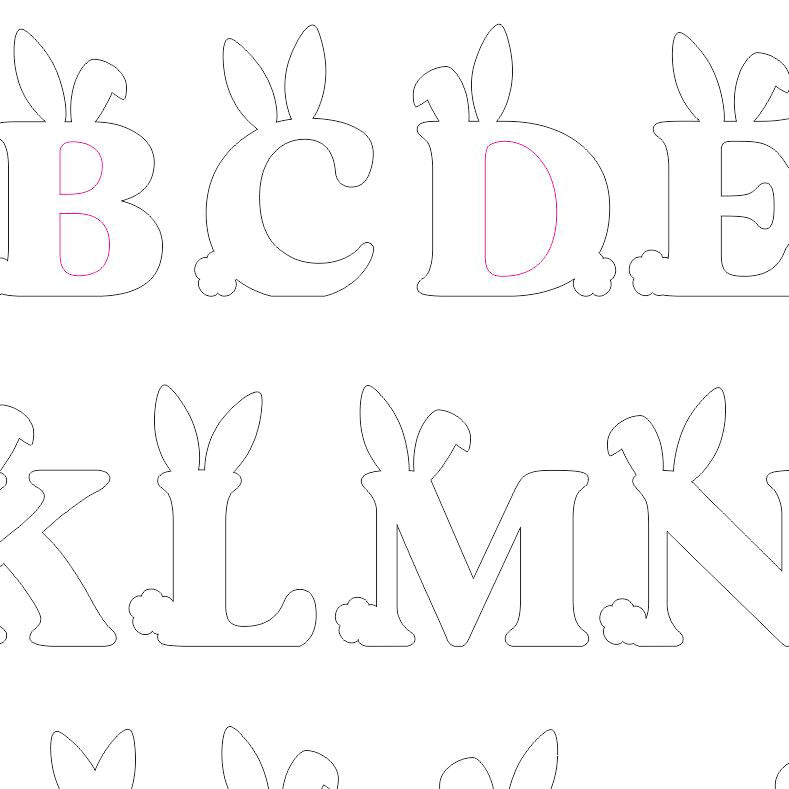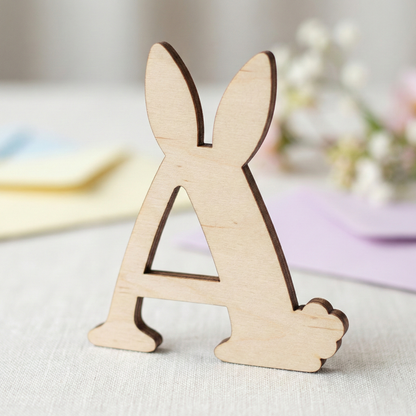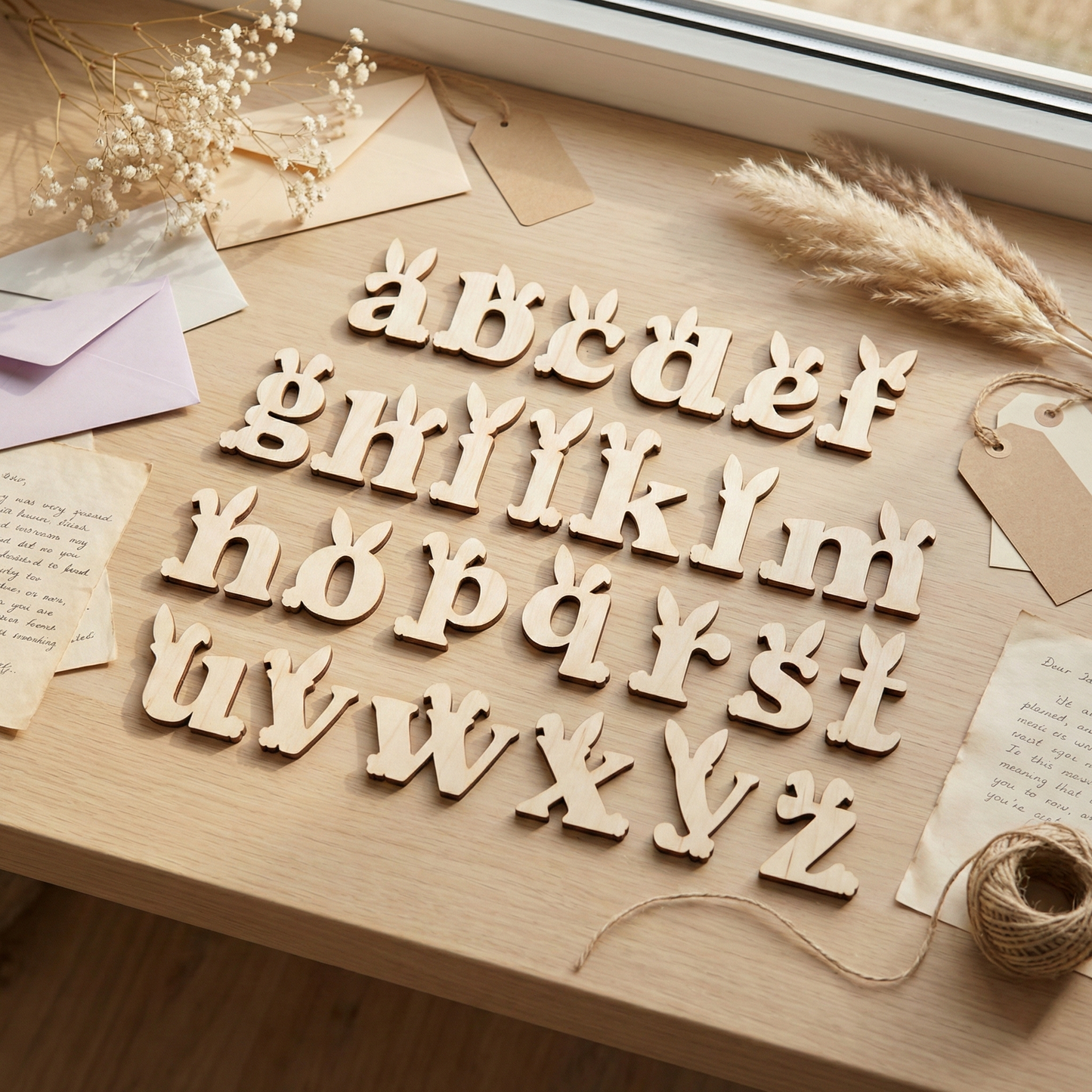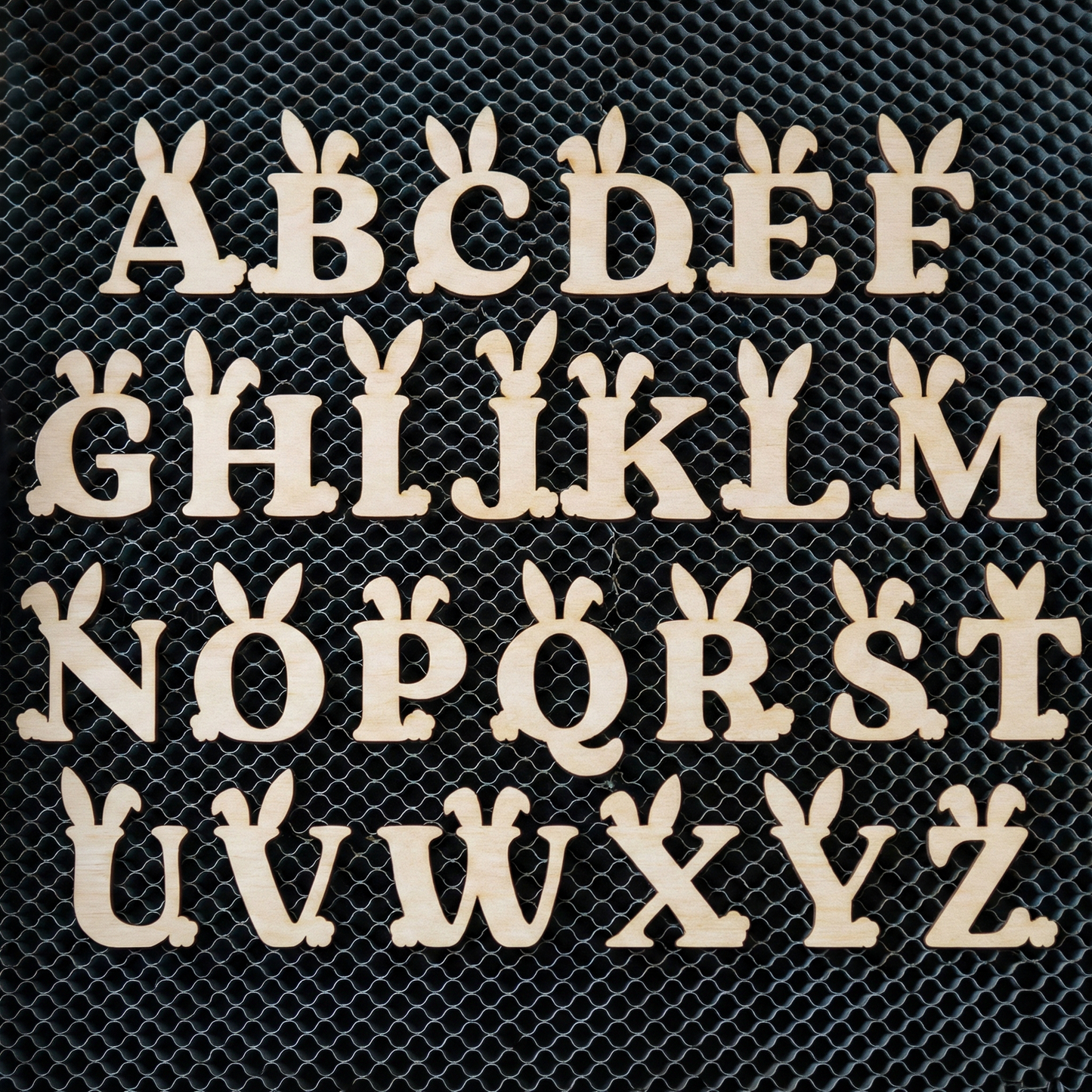
Este archivo de corte láser de letras decorativas de Pascua es un alfabeto SVG diseñado para crear letras de madera con orejas de conejo utilizando una máquina de corte láser. El diseño presenta trazados vectoriales limpios y formas de letras cons...